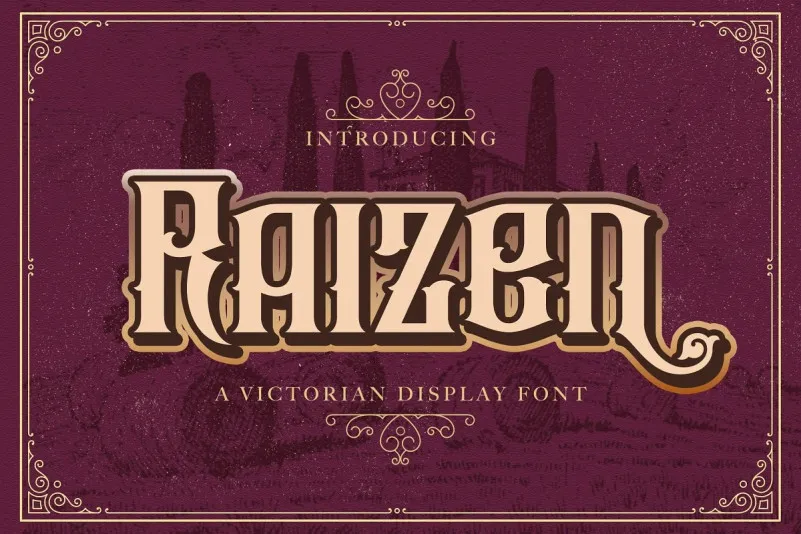
Raizen Font – Fonte Grátis
Raizen Font
A Raizen Font é uma opção única para os amantes do estilo Blackletter. Adotando elementos fluidos e curvos de tipos romanosesque, ela combina-se com o Gothic estilo Blackletter, criando um tipo que transmite um toque atraente e nostálgico. Esta fonte inspira-se em desenhos tatuados vintage, sendo extremamente impressionante tanto no formato romântico quanto na sua atenção aos detalhes. A Raizen tem uma aparência que se encaixa perfeitamente em designs modernos e clássicos, fornecendo um visual atraente e único. Ideal para usar em diversos estilos gráficos, seja em logotipos ou materiais de publicidade, ela é certamente uma escolha ideal.